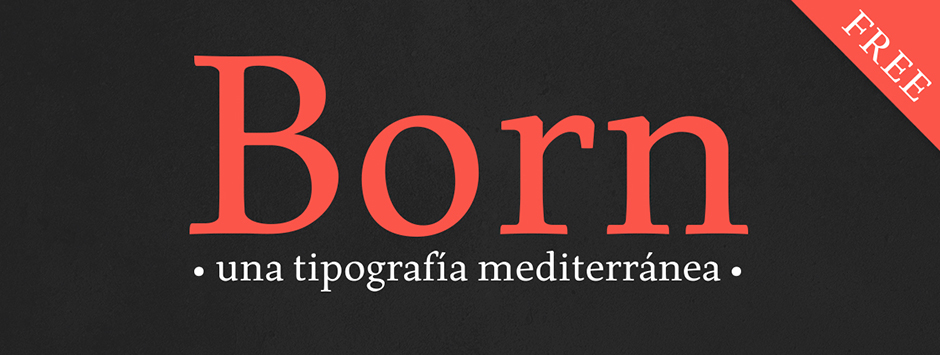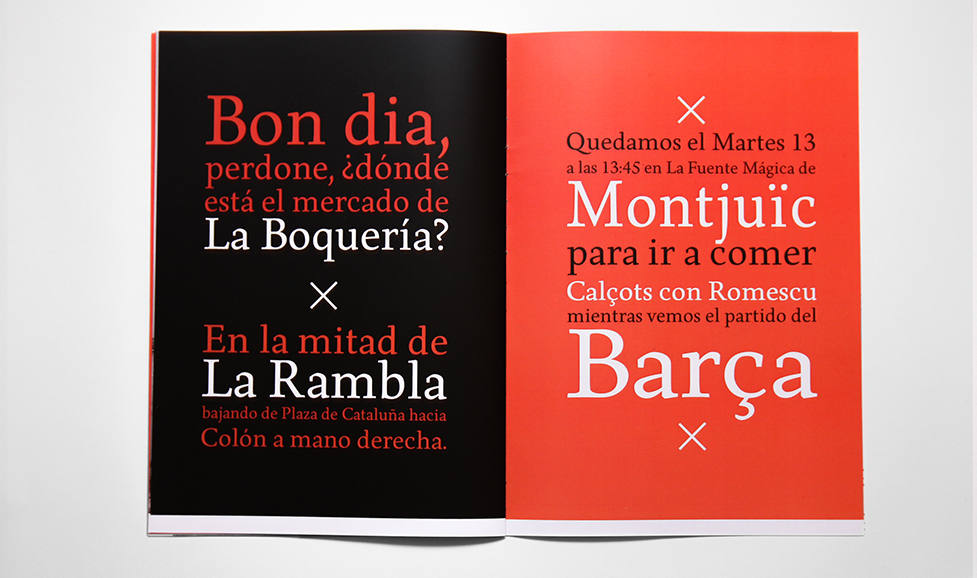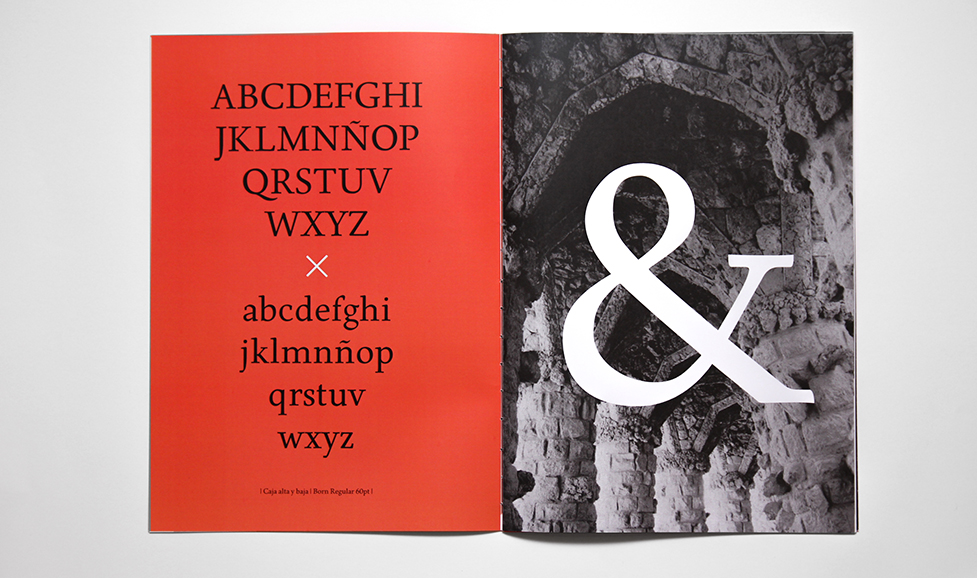
El diseñador riojano Carlos de Toro nos presenta este fantástico trabajo tipográfico titulado Born. Una tipografía totalmente gratuita con un acabado abierto, fresco y actual.
Born es mucho más que una tipografía, es también una historia; La de Carlos en el año 2013. La historia de una mudanza a la gran ciudad, el resultado de conocer grandes personas de todas partes del mundo y también sus culturas, de conversaciones en clases, bares, trenes… de compartir momentos, experiencias, conocimientos… Born es el resultado de todas estas vivencias y personas: y ahora yo comparto contigo este pedacito de historia.
Born es una tipografía humanista que sigue las formas caligráficas tradicionales en su base pero con algunas novedades en sus remates, trazos y gotas que aportan un aspecto más abierto, fresco y actual. Además posee una elevada altura de x, de modo que ofrece una alta legibilidad incluso a tamaños pequeños
Born Regular incluye un total de 262 caracteres:
Caja alta, Caja Baja, Caracteres alternativos de las anteriores, Ligaduras corrientes, Numerales mayúsculos y Símbolos y signos de puntuación.